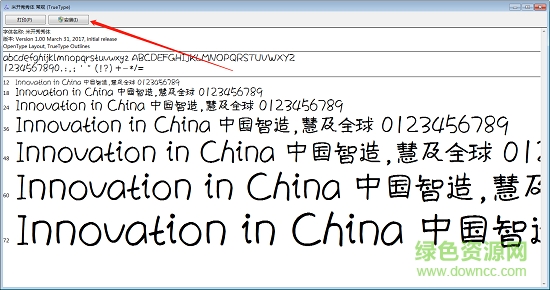
米開秀秀體字體是一款充滿童趣的字體,字體的設計以簡約為主,整個字體的形態(tài)類似于小時候的寫的字,帶有一點點的趣味,整個字體的排版看起來比較豐富,喜歡的用戶快來綠色資源網下載吧!
米開秀秀體字體是一款ttf格式的手寫字體。這款字體并不拘束,書寫起來也沒有什么規(guī)律,但是從視覺效果上來看還稱得上是整齊;而且它還有一點點的童趣,像是小學生書寫數來的,很適合用在小孩的物品上。
米開秀秀體字體美麗秀麗,在進行書寫的時候能夠帶給你十分整潔的視覺體驗,同時也可以運用到廣泛的各類媒體制作中哦!